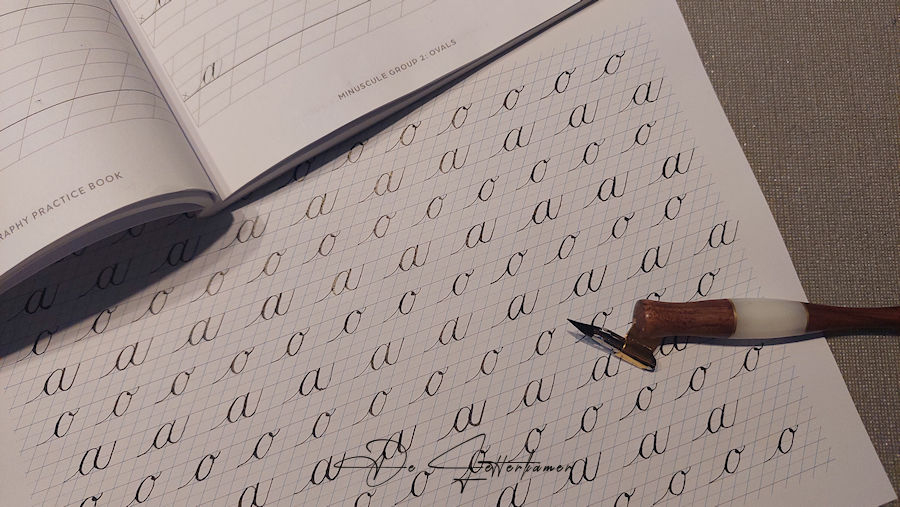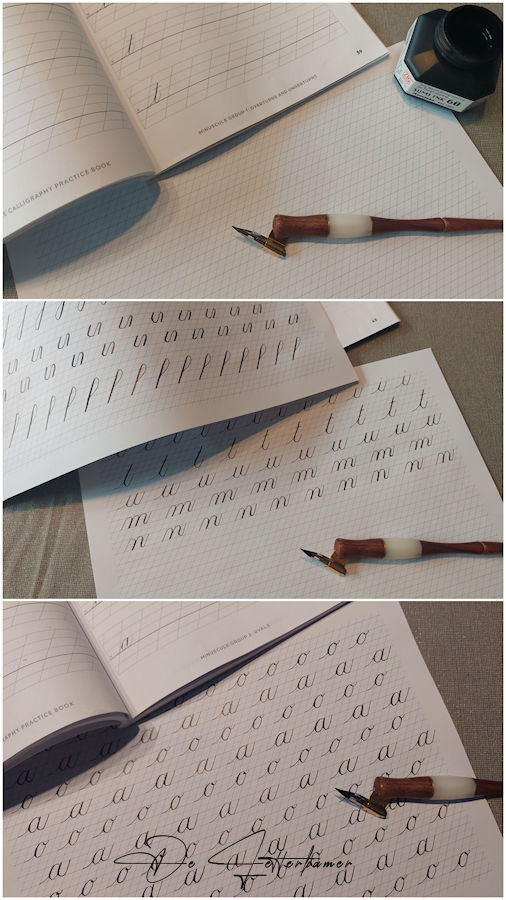
Er is 1 week voorbij gegaan. De tijd gaat snel, te snel. De avond valt vlug, de herfst komt naderbij. Ik neem mijn materiaal bij de hand, de penhouder ligt goed in de hand, de inkt schrijft vlot. We gaan eerst de basisvormen oefenen dit als opwarmingsoefening.
Mijn boek (*zie bron) ligt open “Group 2: ovals”, dit zijn de letters o, a, e, d en c. Ik ben eerst begonnen met de letters “o en a”, de nib heb ik er nu verder in de penhouder gedaan zoals mij aanbevolen was. Nog steeds nib Nikko G, ik ben daar heel tevreden over, alhoewel ik wel eens een andere zou willen proberen.
Dit is nu de 1ste keer, een gans blad geoefend, het gaat al een stuk beter. Ik heb zelf een systeem voor mezelf uitgekozen zodat het niet eentonig wordt.
Ik oefen nu eerst mijn basisvormen als opwarming dan kies ik uit de groep 2 à 3 letters. Steeds hetzelfde is me vlug te saai. Wie mij wat kent, weet dat, variatie is nodig.
“Na een tijdje merkte ik dat kalligrafie meer was dan alleen mooie letters schrijven. Het is een moment waarop ik rustig kan worden en mijn aandacht volledig bij het papier ligt. Elke beweging van de pen heeft invloed op het eindresultaat.”
Zo, na een uurtje is het voor mij genoeg geweest, tijd om te rusten. En mijn pen ziet me volgende keer weer op een rustig moment.